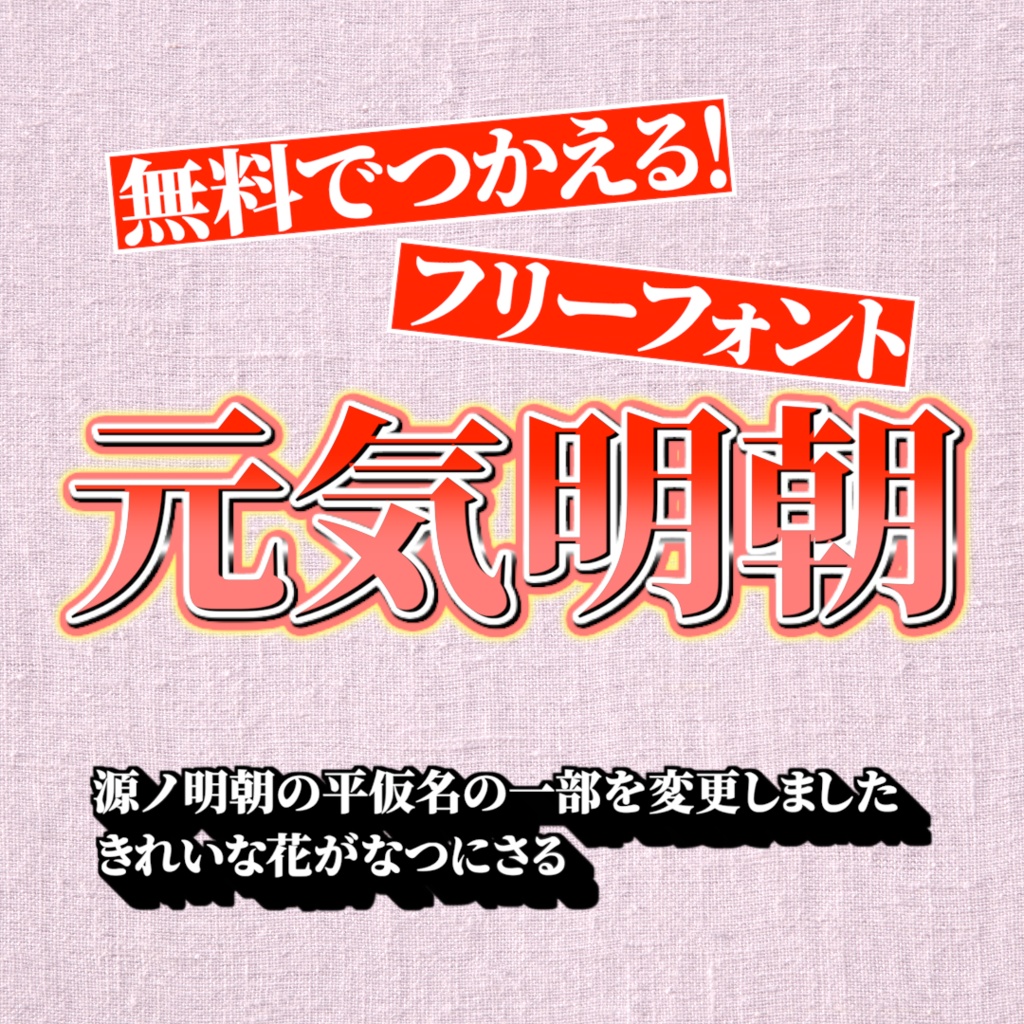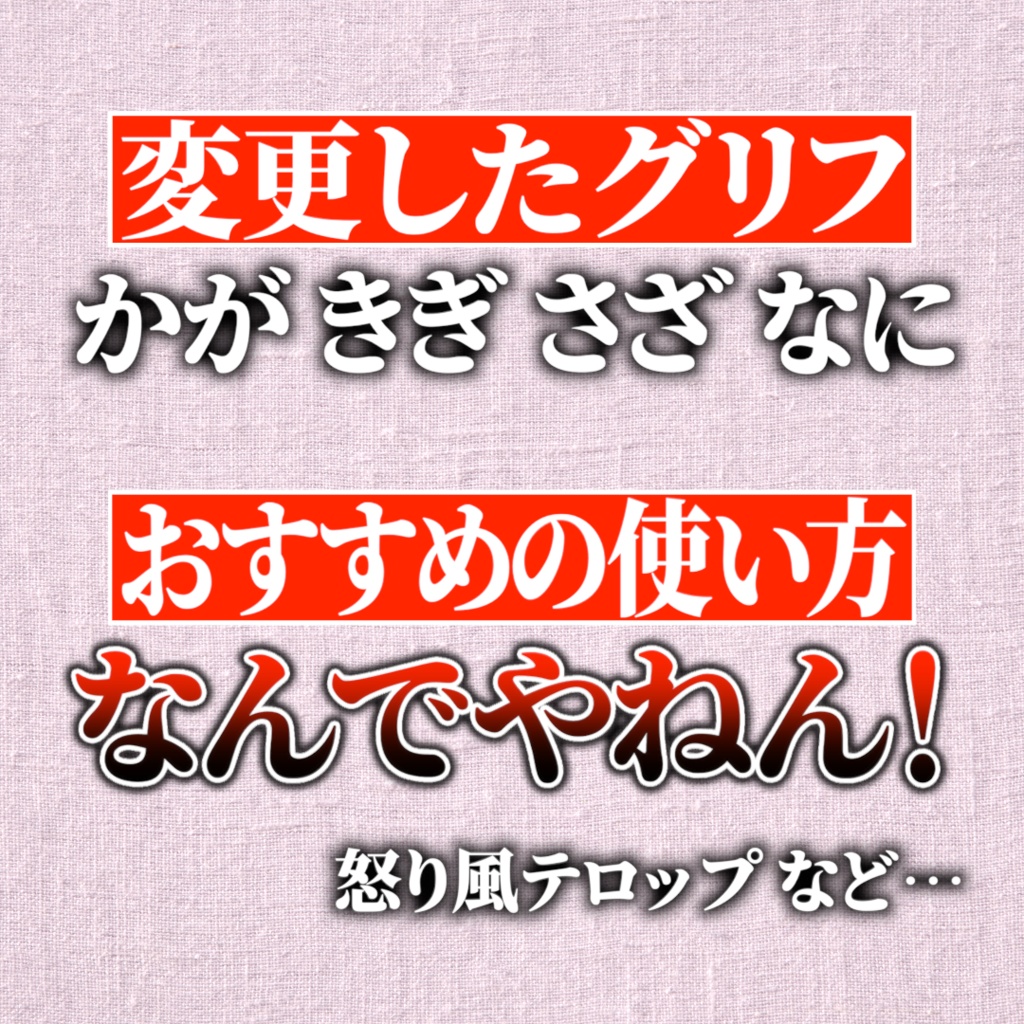
【フリーフォント】元気明朝
◉詳 細 源ノ明朝の一部グリフを改変し制作したフォントです。 ◉ライセンス 本フォントは、SIL Open Font License 1.1に基づき公開されています。 非営利・商用を問わず、無償でご利用いただけます。 ◉当フォントにつきまして 元気明朝は「源ノ明朝 (Source Han Serif)」をベースに制作・改変いたしました。 元フォントの制作者の皆様に深く感謝いたします。 源ノ明朝 (Source Han Serif) https://source.typekit.com/source-han-serif/jp/ ◉投げ銭版につきまして 無償版と投げ銭版の間で、フォントの機能などに差は一切ございません。 制作活動へのご支援をいただけますと幸いです。